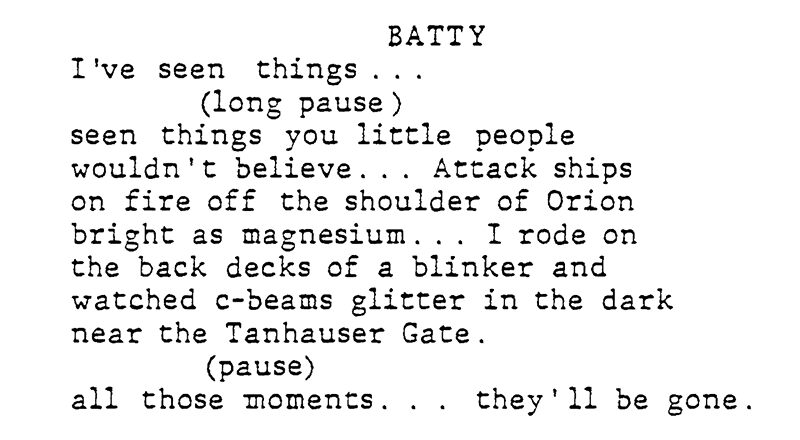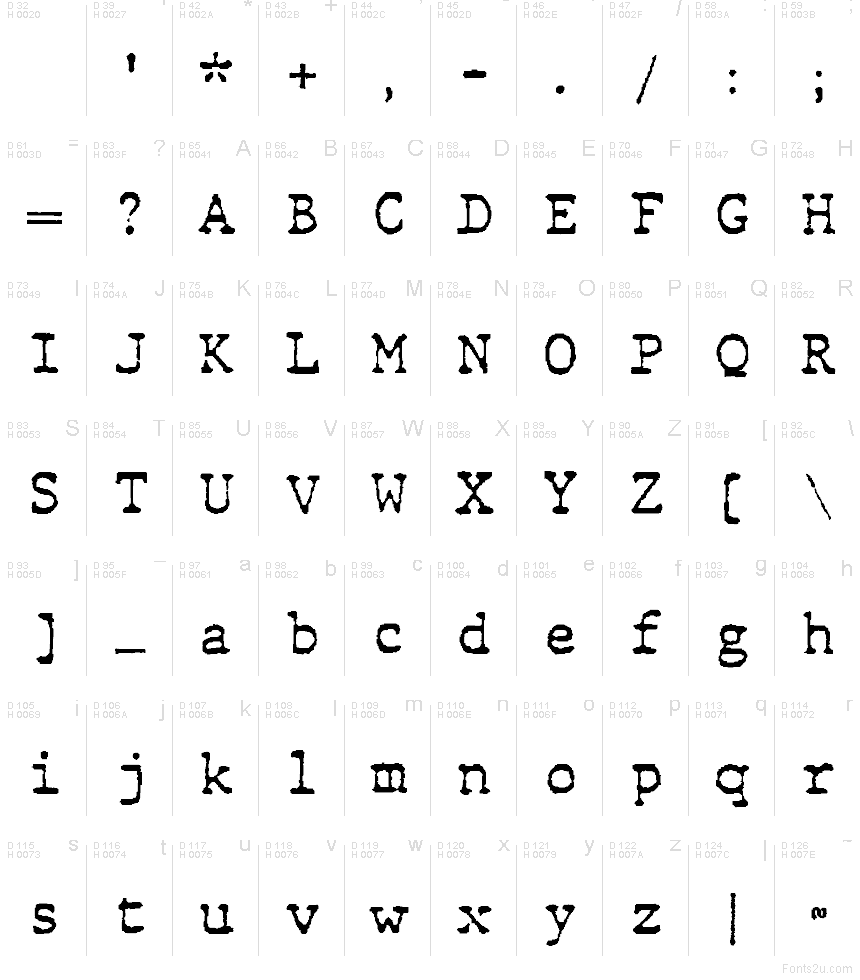
Blade Runner Screen Play je bezplatné patkové písmo typu display s opotřebovaným vzhledem, připomínajícím starou fotokopii. Písmena působí masivně a literárně, mají měkké okraje narušené inkoustem a robustní tvary, díky nimž vypadají, jako by byly vytrženy ze starého scénáře nebo titulkového bloku.
Hodí se na plakáty, knižní obálky, filmové titulky, ziny a nápojové lístky, kde potřebujete bezplatný font s drsnějším nádechem, který však nesklouzne ke klišé hororových písem. Protože si tvary i přes texturu zachovávají čitelnost a známý ráz, funguje skvěle také v krátkých nadpisech, úvodech kapitol či iniciálách, kde tato „ošoupaná“ textura udělá většinu práce.
Blade Runner Screen Play je oživením zapomenutého, dnes již nepoužívaného (a neznámého) psacího písma z 80. let, jehož autorem je Gary Stephens.